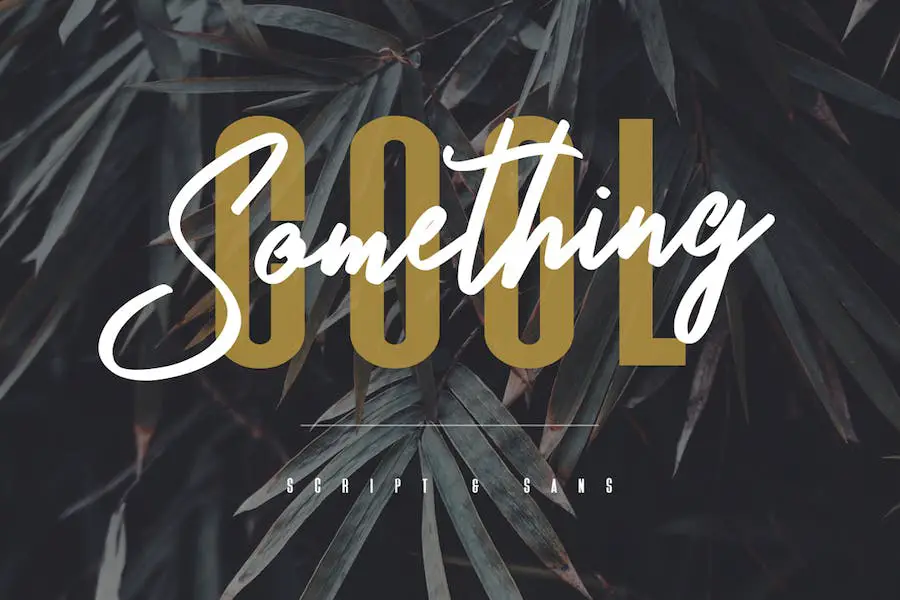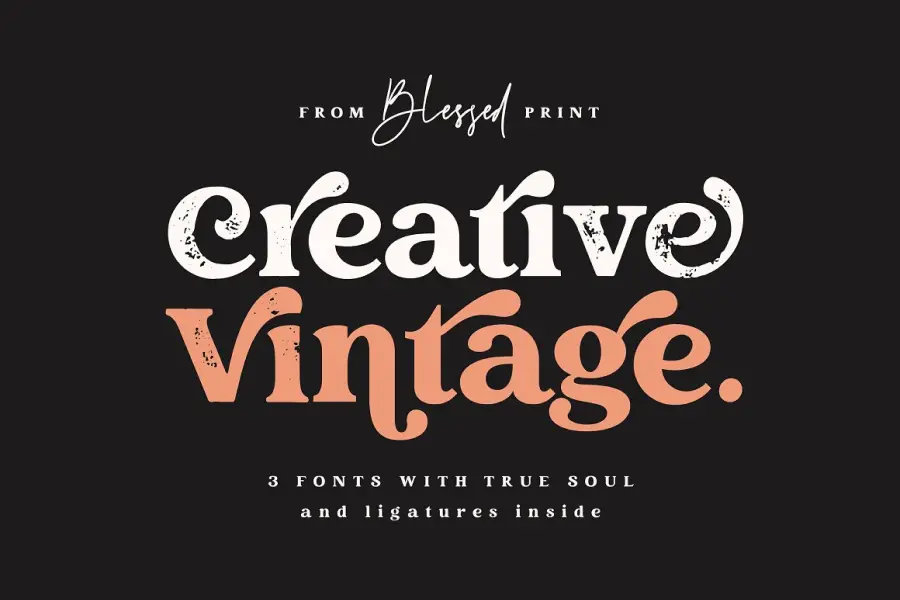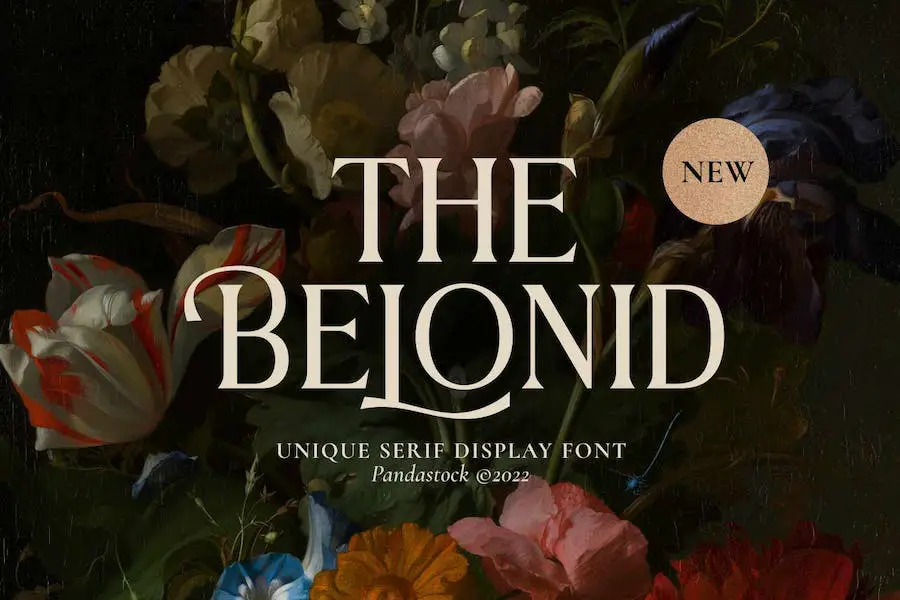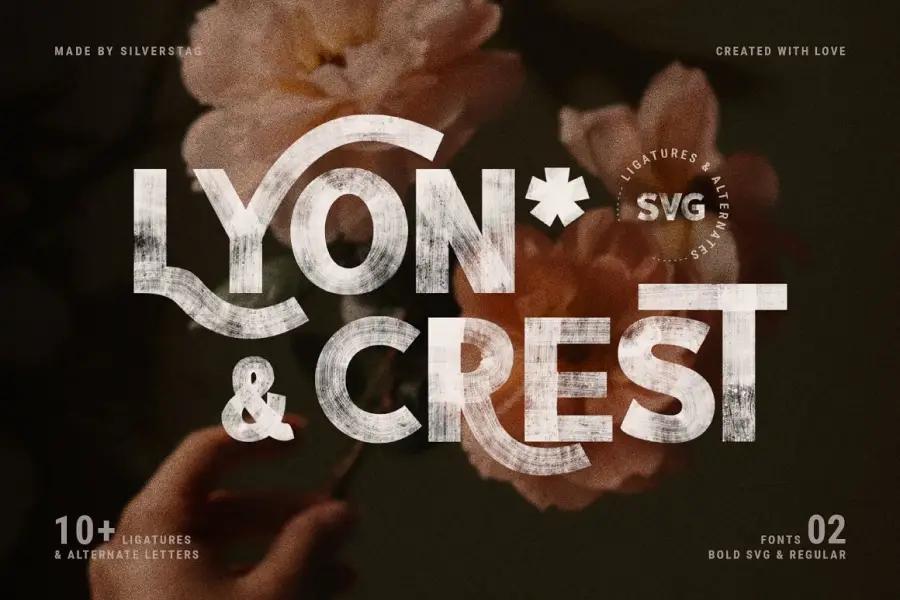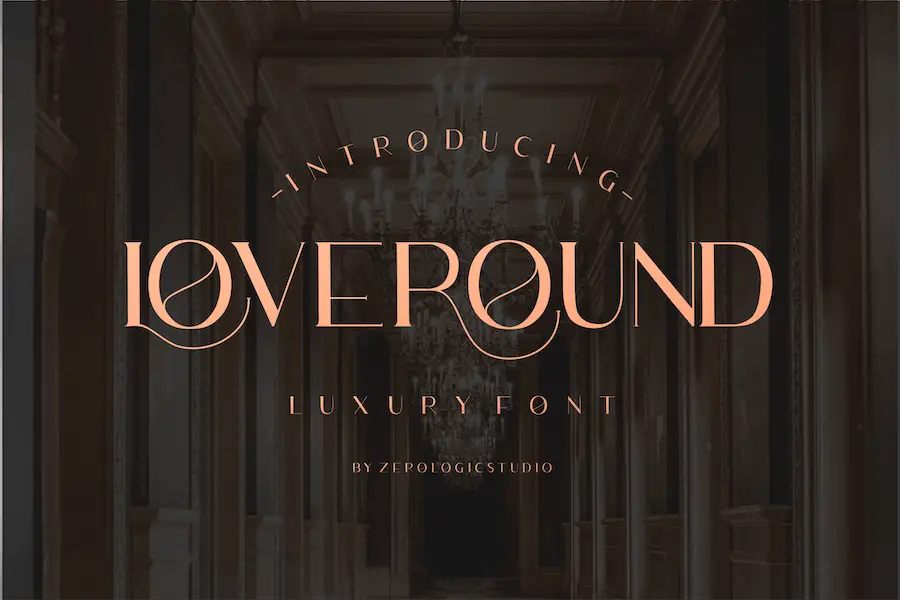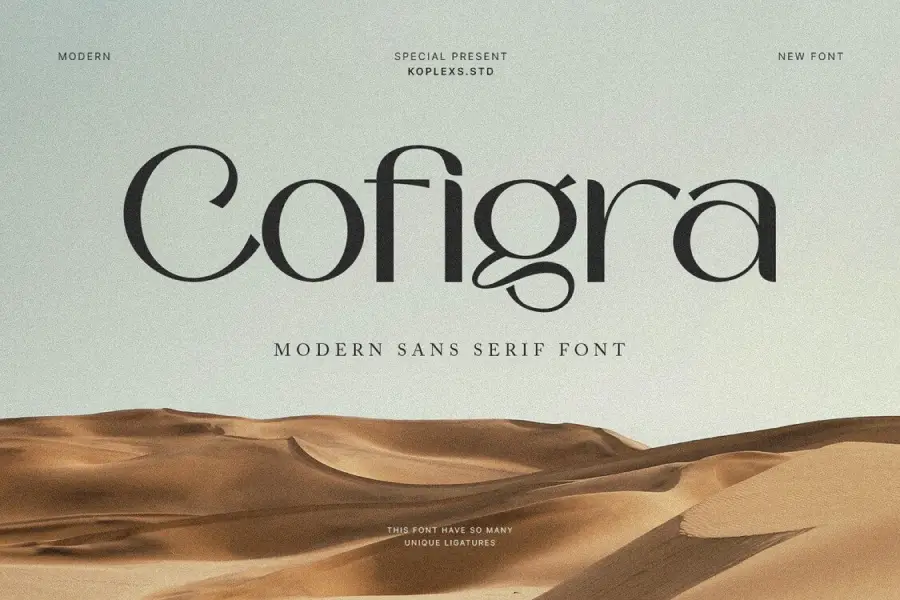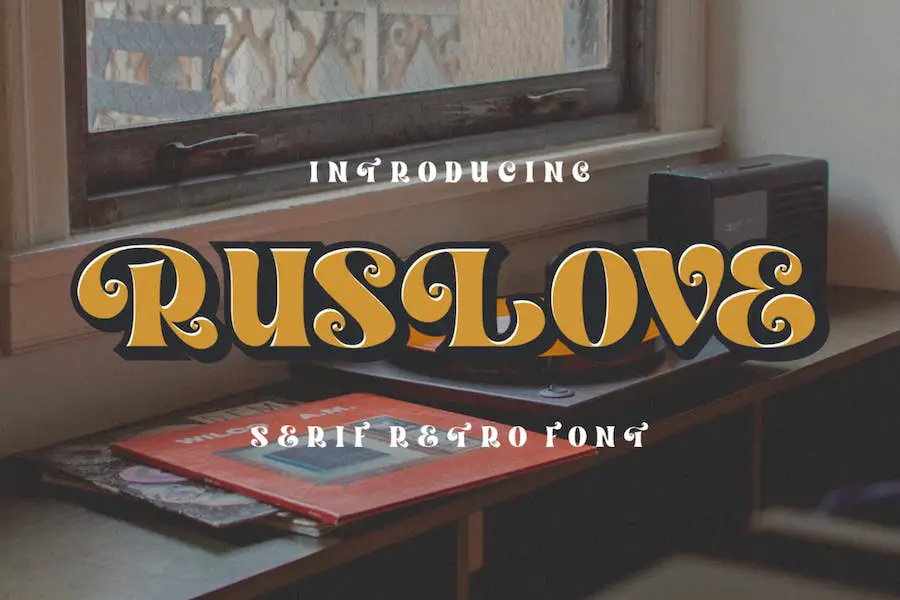
I 15 migliori font fantastici del 2023 (gratuiti e professionali)
Pubblicato: 2023-04-18Ti sei mai ritrovato a passare ore a scorrere le opzioni dei caratteri, cercando di trovare quello perfetto per il tuo progetto?
Non guardare oltre! In questo post del blog, abbiamo compilato un elenco dei 15 migliori caratteri fantastici che porteranno il tuo gioco di design al livello successivo.
L'uso della tipografia può avere un impatto significativo sull'estetica complessiva e sulla leggibilità di qualsiasi contenuto, sia esso un sito Web, un poster o una grafica per social media. Sapevi che gli studi suggeriscono che l'uso del carattere giusto può aumentare la velocità di lettura fino al 25%?
Con così tante opzioni disponibili, può essere travolgente scegliere quella giusta. Ma non preoccuparti: ci pensiamo noi!
In questo articolo, ti presenteremo i 15 migliori caratteri fantastici perfetti per qualsiasi progetto di design. Dai classici serif ai moderni sans-serif, abbiamo curato un elenco di caratteri che sicuramente faranno risaltare il tuo testo.
Quindi, senza ulteriori indugi, tuffiamoci ed esploriamo questi fantastici font!
I migliori font fantastici premium
In questo articolo condivideremo alcuni dei caratteri più unici ed eleganti disponibili sul mercato. Ma non limitarti a crederci sulla parola, lo sapevi che l'utilizzo di caratteri visivamente accattivanti può effettivamente aumentare la leggibilità e il coinvolgimento dei tuoi contenuti?
Secondo uno studio dell'Università del Michigan, i lettori erano più propensi a ricordare le informazioni quando erano presentate in un carattere facile da leggere e visivamente piacevole.
Allora perché accontentarsi di caratteri ordinari quando puoi elevare il tuo gioco di design con questi fantastici caratteri premium? In questo articolo, mostreremo i migliori caratteri per varie esigenze di progettazione, inclusi loghi, siti Web, grafica per social media e altro ancora. Immergiamoci!
Esposizione Fleur
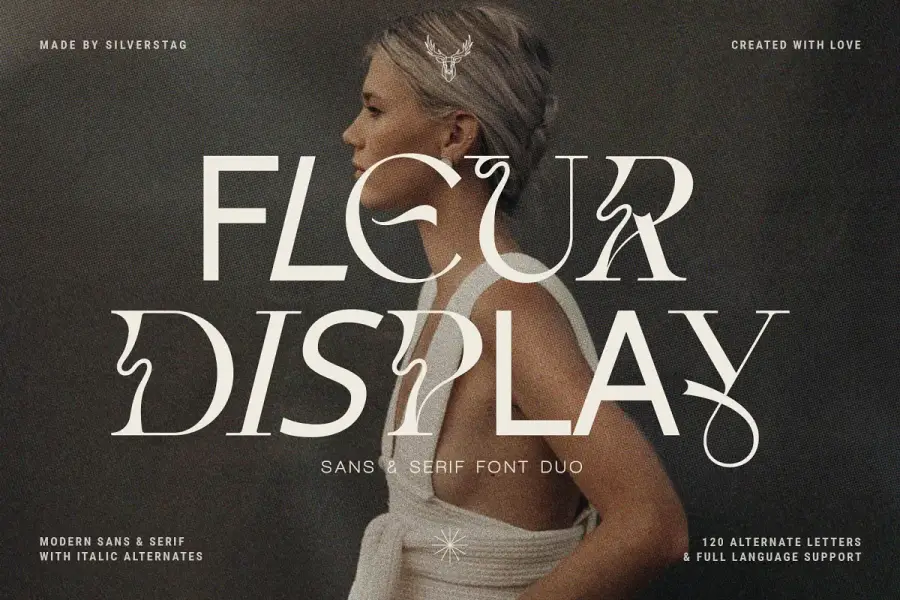
Il display Fleur è un font che viene fornito con supporto linguistico completo, numeri e punteggiatura. una delle sue caratteristiche più importanti è l'inclusione di lettere alternative a cui è possibile accedere tramite la maggior parte delle app per computer e Canva. quindi puoi usarlo per fantastici caratteri per Canva.
Questo carattere è perfetto per coloro che vogliono aggiungere un tocco di eleganza e raffinatezza ai loro disegni. Il suo design elegante e moderno può essere utilizzato per una varietà di scopi, che si tratti di creare loghi accattivanti o progettare bellissimi inviti.
Nel complesso, Fleur Display è una scelta eccellente per chiunque cerchi un font di alta qualità che sia versatile e facile da usare. Con le sue istruzioni dettagliate e il supporto linguistico completo, sarai in grado di creare fantastici design in pochissimo tempo. Che tu sia un grafico professionista o che sia appena agli inizi, vale sicuramente la pena prendere in considerazione questo tipo di carattere.
Gemello Denko
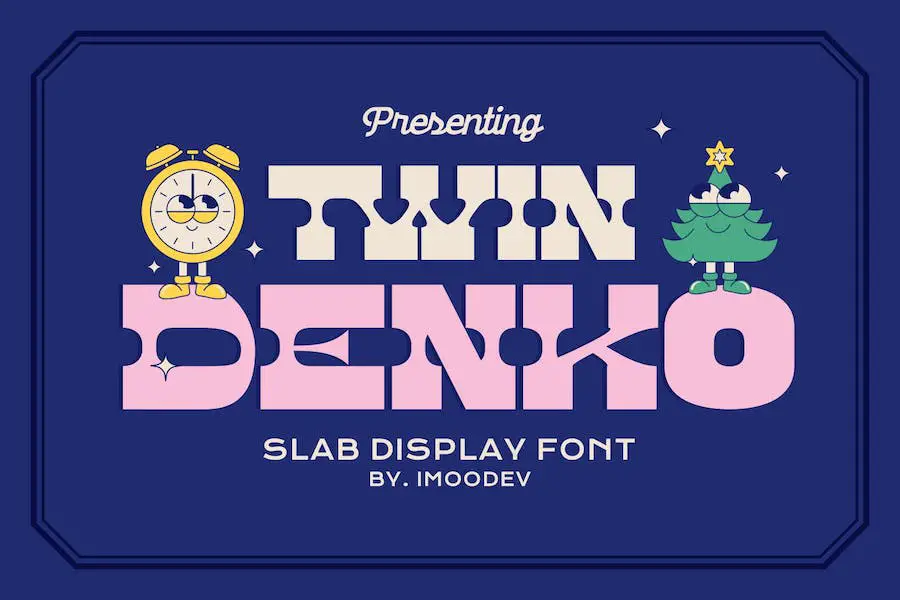
Twin Denko è un carattere moderno ed elegante che possiede curve morbide e belle legature, producendo un aspetto attraente e autentico. Questo carattere versatile può essere utilizzato in vari progetti, come loghi, fotografie, inviti, confezioni di prodotti, branding, riviste, tazze e altro ancora. Il suo appeal visivo e la sua adattabilità lo rendono ideale sia per grandi che per piccoli formati.
La bellezza di Twin Denko sta nella sua semplicità. Con linee chiare e curve morbide, aggiunge un tocco di eleganza a qualsiasi progetto di design. Questo tipo di carattere è progettato per migliorare l'aspetto visivo del tuo lavoro mantenendo un livello di leggibilità che garantisce che il tuo messaggio arrivi forte e chiaro. L'elegante e moderno Twin Denko farà sicuramente girare la testa e impressionerà chiunque lo veda.
La versatilità del carattere lo rende una scelta eccellente per vari progetti, rendendolo un investimento prezioso per i grafici di tutto il mondo. Che tu stia lavorando a un logo per una startup o progettando il layout di una rivista, Twin Denko ti copre. È anche un'ottima opzione per creare grafiche accattivanti per i social media o progettare un'etichetta di prodotto che si distingua sullo scaffale.
PRESTO
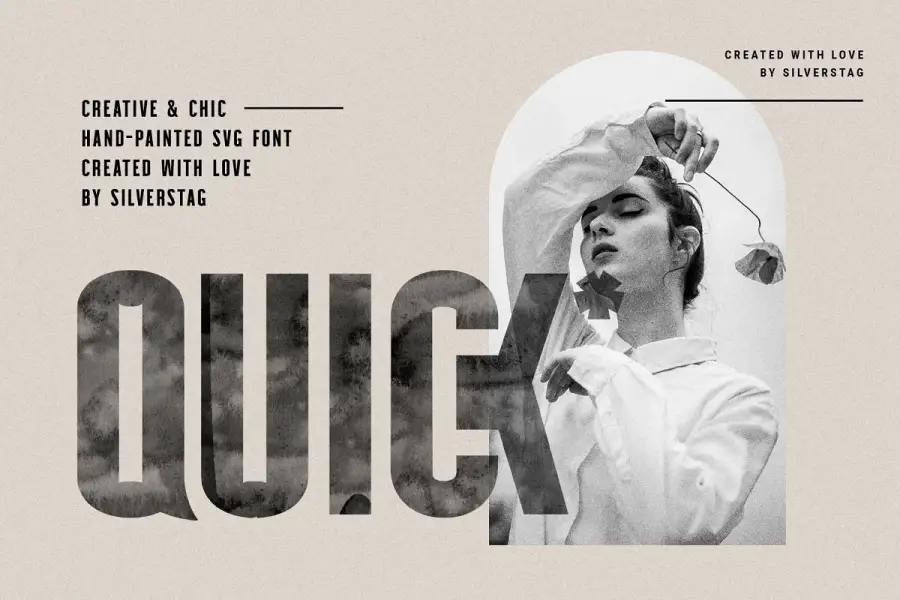
QUICK è un nuovo pacchetto di font SVG dipinto a mano che offre un aspetto unico e distintivo ai tuoi progetti. Questo pacchetto di caratteri offre un vero effetto acquerello che eleverà il tuo lavoro e ti aiuterà a creare nuovi fantastici design. È ideale per Cool Fonts for Tattoo.
Una delle caratteristiche più importanti di QUICK è la sua capacità di aggiungere una texture acquerello realistica alla tua tipografia. Il design dipinto a mano gli conferisce un aspetto davvero unico che lo distingue dagli altri caratteri. Con questo pacchetto di font, puoi aggiungere un tocco di creatività ai tuoi progetti, facendoli risaltare dalla massa.